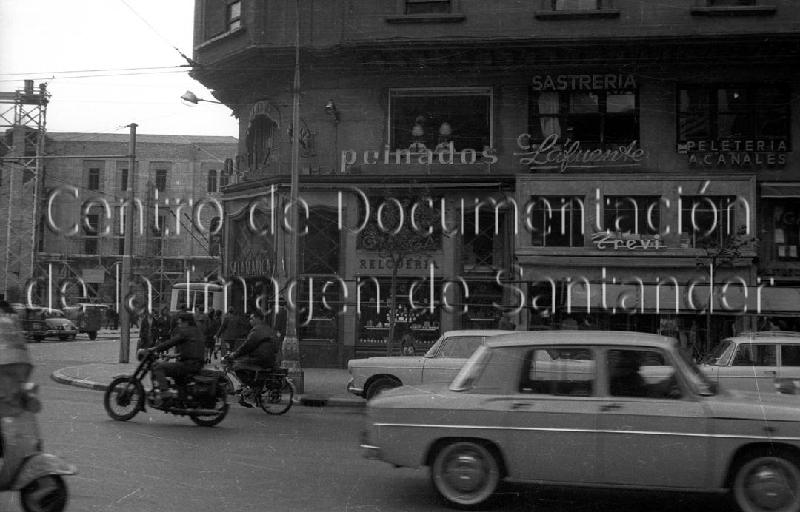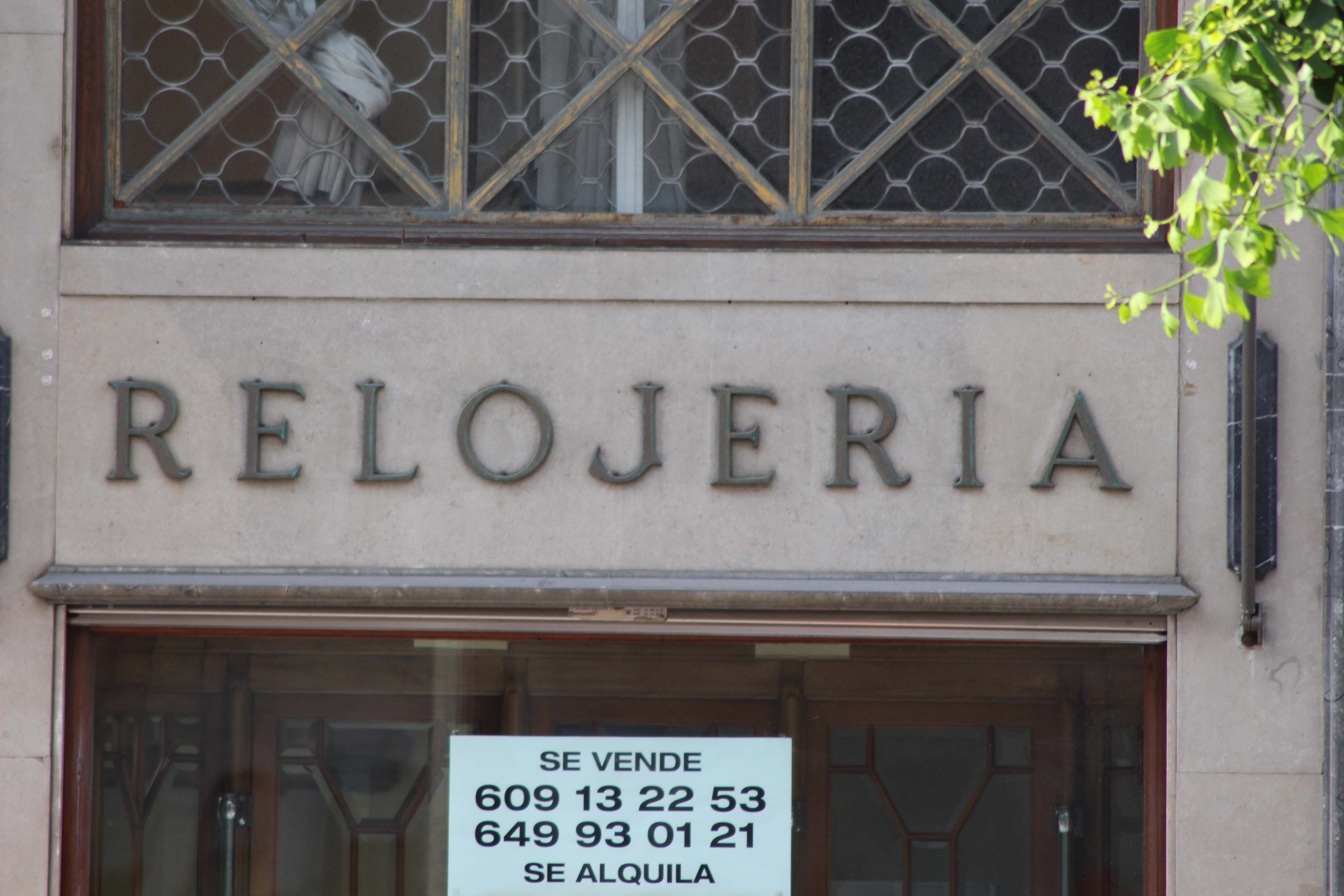
Joyería Salamanca
Antes de la declaración del Estado de Alarma por la pandemia del COVID-19 en marzo, pudimos rescatar el rótulo del Bar Gelín. Con la vuelta a la nueva normalidad ha vuelto la rutina a las calles, y con ella las obras y reformas en locales comerciales. De hecho nos informaron de que el rótulo de «La Mejillonera» estaba siendo desmontado a martillazos. No se pudo hacer nada para salvarle de acabar siendo chatarra.
Uno de los rótulos que ya estaba en seguimiento era el de la Joyería Salamanca. El año pasado con motivo de la campaña de crowdfounding que estaba en marcha para la publicación del libro, inicié una acción para ir dejando avisos de rescate en locales comerciales cerrados.
La Joyería Salamanca cerró sus puertas en 2015, tras más de 70 años abierta en el local de Calvo Sotelo, frente al Ayuntamiento. Aunque sus raíces se remontan a finales del s. XIX, es en 1936 cuando llegan a Santander Urbano Salamanca y Justina Alonso abriendo una pequeña joyería en la calle San Francisco. Tras el incendio de Santander de 1941, se vieron obligados a instalarse en un barracón del Paseo Pereda. Y es en 1950 cuando inauguran el local de Calvo Sotelo en esquina con Isabel II. Serán después los sobrinos de estos quienes siguieran con el negocio hasta su cierre.
El local tenía un aspecto clásico, con mucho detalle en su interior. Espacios, suelos, moldura o muebles diseñados ad hoc. Algunos de ellos al cierre fueron vendidos. En el exterior el juego de letras expuesta era con dos tipos. Roman para las que estaban encima de las ventanas y Palo Seco, con iluminación, para el rótulo principal que estaba encima de la puerta.
1964. Fondo Pablo Hojas / Centro de Documentación de Imagen de Santander.
El rótulo principal fue sustituido en la última reforma por su mal estado, incorporando uno de bronce en una tipo Script.
Lo que perduró hasta su cierre son por tanto, es todo el juego de letras ORIGINALES de bronce de las ventanas:  SALAMANCA, JOYERÍA, RELOJERÍA.
La historia del rescate es de las que gustan. Durante la presentación del libro, en febrero, pude hablar con Asun, una de las sobrinas. A través de otro familiar le llegó la existencia del proyecto y quiso conocer más. Fue un placer poder explicar de primera mano que es lo que se busca y la filosofía del proyecto. Además vio que era uno de los rótulos que aparece en el libro. Le gustó la idea y como la decisión no era única, tuvo que consultarlo. Después vino la pandemia… Y volvemos a hoy. La semana pasada, finales de mayo (Fase 2) por aviso, me acerqué a «Regalos Pombo» que está de obras para ver el estado de los cristales que decoraban la fachada. Dichos cristales serán preservados, por cesión de César Pombo.
A la vuelta pasé por la Joyería y vi que las letras ya no estaban. Pregunté al jefe de obra y me dijo que se las han dado a una de las propietarias. A los dos días me llamó Asun para decirme que desde la familia querían dar las letras al proyecto, para su preservación. Y así fue.
Las letras tienen una medida de unos 30 cm de alto, y van firmadas por F. Ranninger. (ya estoy buscando información de este taller)
Y así es como se han salvado de desaparecer, al contrario que «La Mejillonera» pasando junto a otros rótulos a ser preservados. La colección está aumentado y ya es necesario poder disponer de un espacio de almacenamiento / trabajo de este Patrimonio Gráfico. Si conocéis algún rótulo en riesgo de desaparecer, avisad de la existencia del proyecto y que se pongan en contacto para poder rescatarlo.